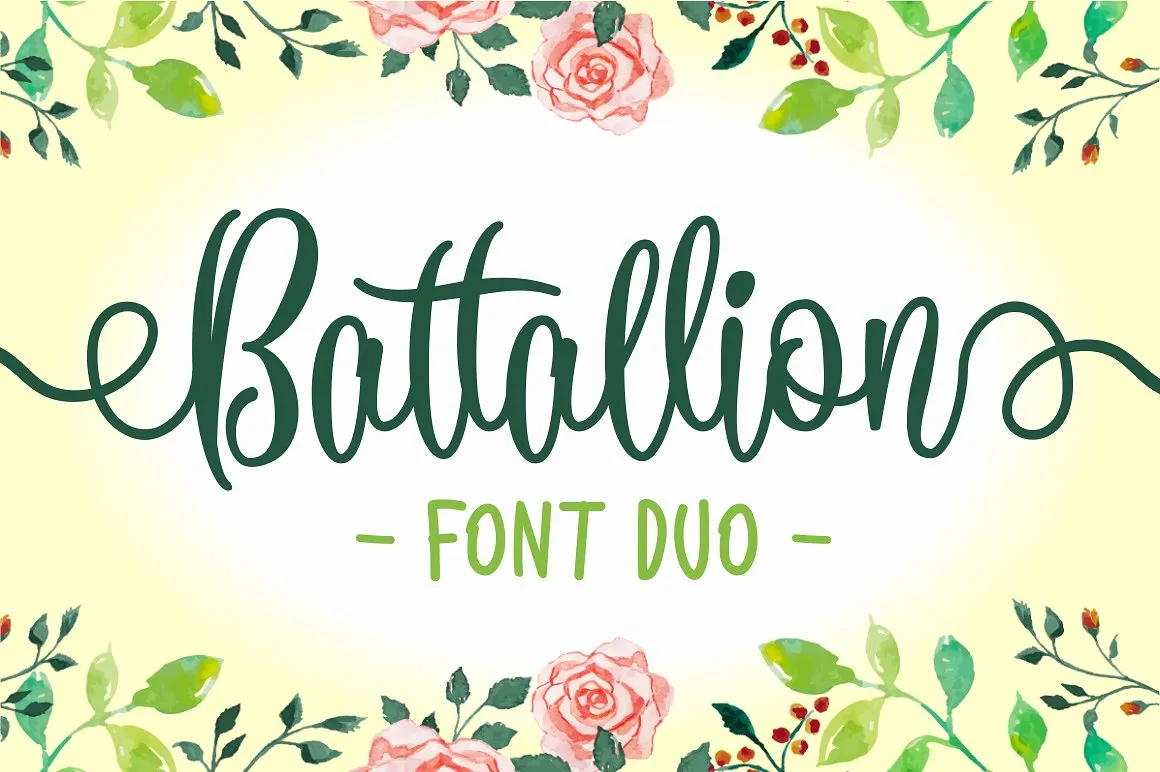
Battallion Script Font – Download Grátis
Battallion Script Font é uma nova fonte que traz a autenticidade das escritas manuscritas junto com os contornos elegantes do moderno desenho de letra. Cada caractere desta fonte tem um toque único, como se fossem escritos por mãos dedicadas, mas também têm as vantagens dos recursos avançados da fonte aberta para que você possa personalizar e moldar cada letra ao seu gosto. Esta fonte é perfeita tanto para aplicativos de design gráfico quanto para uso em logotipos ou letras de casamento. Suas opções flexíveis permitirão que você construa textos elaborados, desde um breve texto de citação até uma carta romântica para seu amado. Com Battallion Script Font, o design gráfico ganha mais expressividade e personalização.